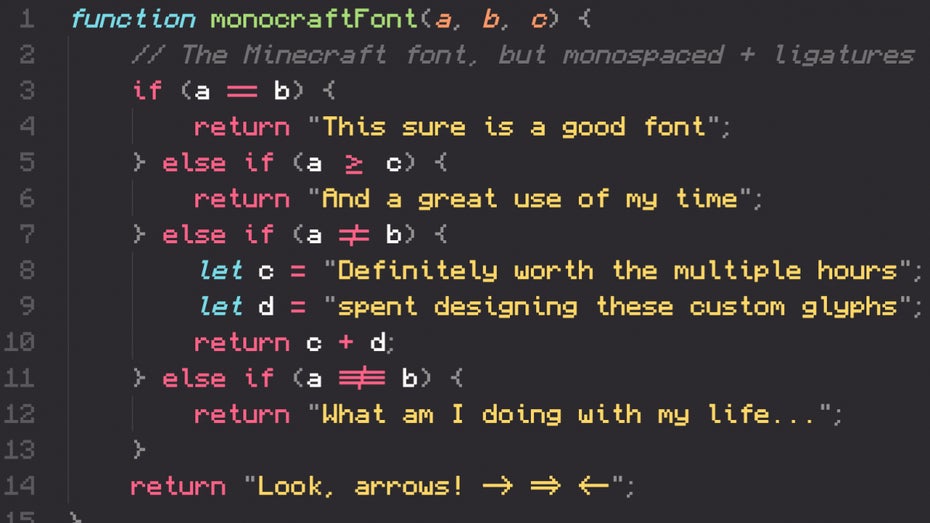
Monocraft ist ein Entwickler-Font für echte Minecraft-Fans
Ein US-Entwickler ist ein derart großer Fan des beliebten Computerspiels „Minecraft“, dass er eine Monospaced-Schriftart fürs Programmieren erstellt hat, die auf der Schriftart von „Minecraft“ basiert.
Eine Minecraft-Schrift für Entwickler. (Screenshot: Idrees Hassan / Github)
„Ich habe diese Schriftart erstellt, weil ich dachte, es würde Spaß machen, zu lernen, wie Schriftarten funktionieren“, erklärt Idrees Hassan gegenüber dem Technologie-Blog Ars Technica. Bestehenden Minecraft-Schriftarten fehlten seiner Meinung nach ein paar Details, wie das richtige Kerning und die richtige Pixelgröße. „Also dachte ich, ich sollte das selbst machen.“
Als das erledigt war, verwandelte er seine Updates in eine „richtige“ Programmierschrift. Außerdem, betonte er, könne er jetzt Minecraft-Plugins in einer Minecraft-Schriftart schreiben.
Zeichen wurden neu gestaltet
Das Ergebnis ist Monocraft. Der Font gibt Programmierer:innen das Gefühl, mitten in der Minecraft-Welt zu sein, während sie ihrer Programmiertätigkeit nachgehen.
Um die Minecraft-Schriftart für Entwicklungszwecke anzupassen, hat Hassan Zeichen neu gestaltet, damit sie in einem Monospaced-Format besser aussehen, und Änderungen vorgenommen, um Buchstaben wie „i“ und „l“ leichter zu unterscheiden.
Außerdem erstellte er neue Programmier-Ligaturen und verfeinerte das Pfeil-Zeichen, um das Lesen zu erleichtern. Als Ligatur wird in der Typografie die Verschmelzung zweier oder mehrerer Buchstaben bezeichnet. Ligaturen werden zur Vermeidung von optischen Lücken im Schriftbild verwendet. Das steigert die Lesbarkeit des Textes und verbessert das Erscheinungsbild.
Retro-Pixel-Art-Stil zieht immer noch
Hassan hat zudem eine authentische Reproduktion der Minecraft-Schrift erstellt, die wie die Schriftart im Spiel über variable Abstände verfügt. Auch diese ist auf GitHub verfügbar.
Der Minecraft-Schöpfer Markus „Notch“ Persson entwarf die Minecraft-Schriftart bereits im Jahr 2008, ursprünglich für ein Spiel namens „Legend of the Chambered“. Sie basiert auf einem Retro-Pixel-Art-Stil, der auf die 8-Bit- und 16-Bit-Konsolenspiele zurückgeht – und hat noch 14 Jahre später eine spezielle Wirkung auf zahlreiche Menschen, wie das Beispiel von Idrees Hassan zeigt.